6 Rekomendasi Font Canva yang Bikin Brand-mu Terlihat MewahÂ
Menjadikan brand-mu terlihat mewah sebenarnya bukan hanya untuk terlihat 'wah' di mata konsumen, tetapi juga merupakan strategi bisnis yang dapat memberikan sejumlah keuntungan. Pertama-tama, kemewahan menciptakan kesan eksklusivitas yang dapat membuat konsumenmu merasa bahwa produk atau layanan yang kamu tawarkan memiliki nilai lebih tinggi. Hal ini dapat meningkatkan persepsi kualitas dan keinginan konsumen untuk memiliki produk tersebut.
Selain itu, brand yang terlihat mewah cenderung lebih mudah dikenali dan diingat oleh konsumen. Desain yang mencerminkan kemewahan dapat menciptakan kesan profesional dan meyakinkan serta memperkuat citra merek di mata publik. Dengan terlihat mewah, sebuah merek juga dapat menarik segmen pasar yang lebih eksklusif, meningkatkan daya tarik pada target konsumen yang memiliki preferensi kualitas dan gaya hidup yang tinggi.
Jika kamu sedang mencari font Canva yang bisa memberikan sentuhan kemewahan pada bisnis-mu di setiap konten yang kamu buat, berikut adalah 6 rekomendasi font yang pas untuk tujuan tersebut.
1. Juana
Ilustrasi font canva (dok. Canva) Juana adalah font yang menggabungkan keanggunan dengan keindahan. Dengan detail yang halus dan elemen dekoratif, Juana memberikan sentuhan klasik yang cocok untuk bisnis yang ingin terlihat mewah. Penggunaan huruf kapital pada Juana memberikan kesan elegan dan eksklusif, sementara kurva yang lembut menambah nuansa feminin dan anggun.
2. Prata
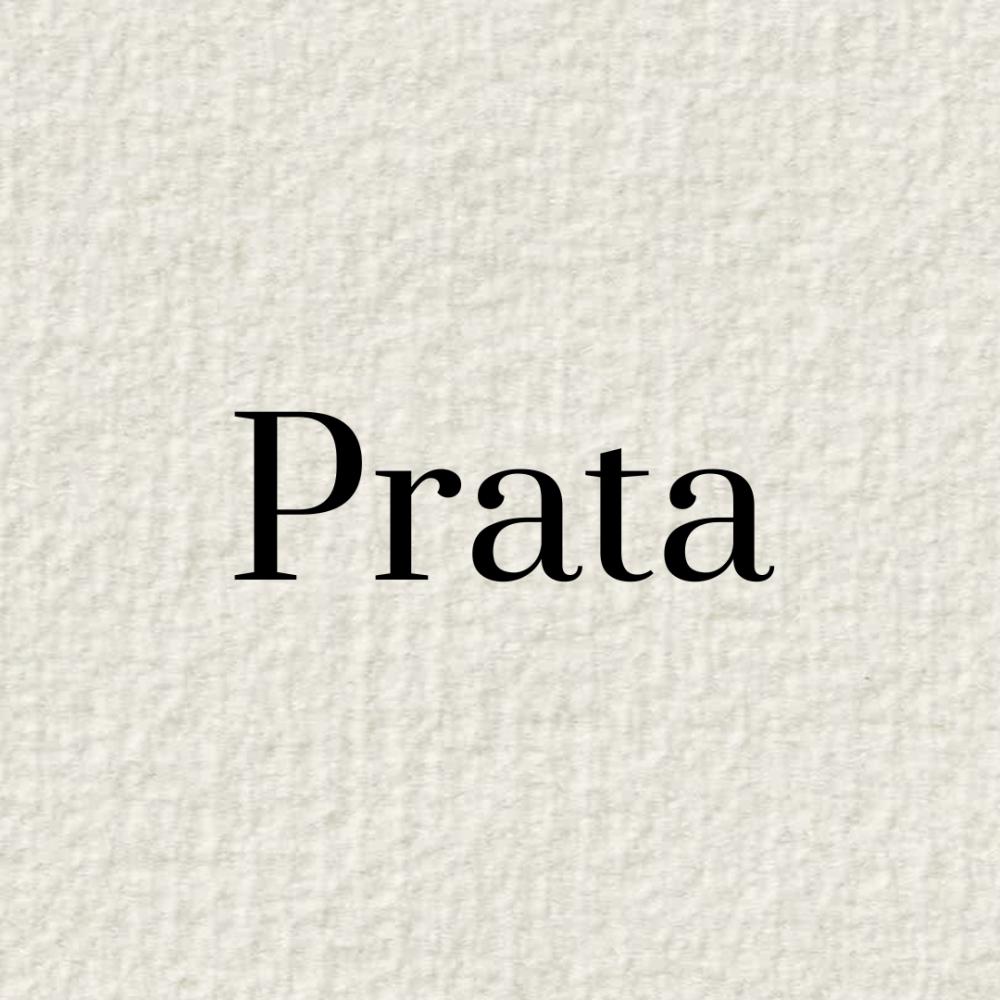
Ilustrasi font canva (dok. Canva) Prata adalah font sans-serif dengan elemen dekoratif yang memberikan sentuhan klasik pada setiap desain. Dengan ketebalan dan proporsi huruf yang seimbang, Prata memberikan kesan profesional dan modern. Cocok digunakan untuk merek yang ingin terlihat trendi namun tetap eksklusif.
3. Niconne
Ilustrasi font canva (dok. Canva) Niconne membawa kita kembali ke era keemasan desain klasik. Font ini memberikan kesan mewah dengan huruf bergaya kapital yang meliuk-liuk. Niconne sangat ideal untuk merek yang ingin memberikan nuansa vintage dan bergaya, menciptakan kesan timeless yang sulit dilupakan.
4. The Seasons
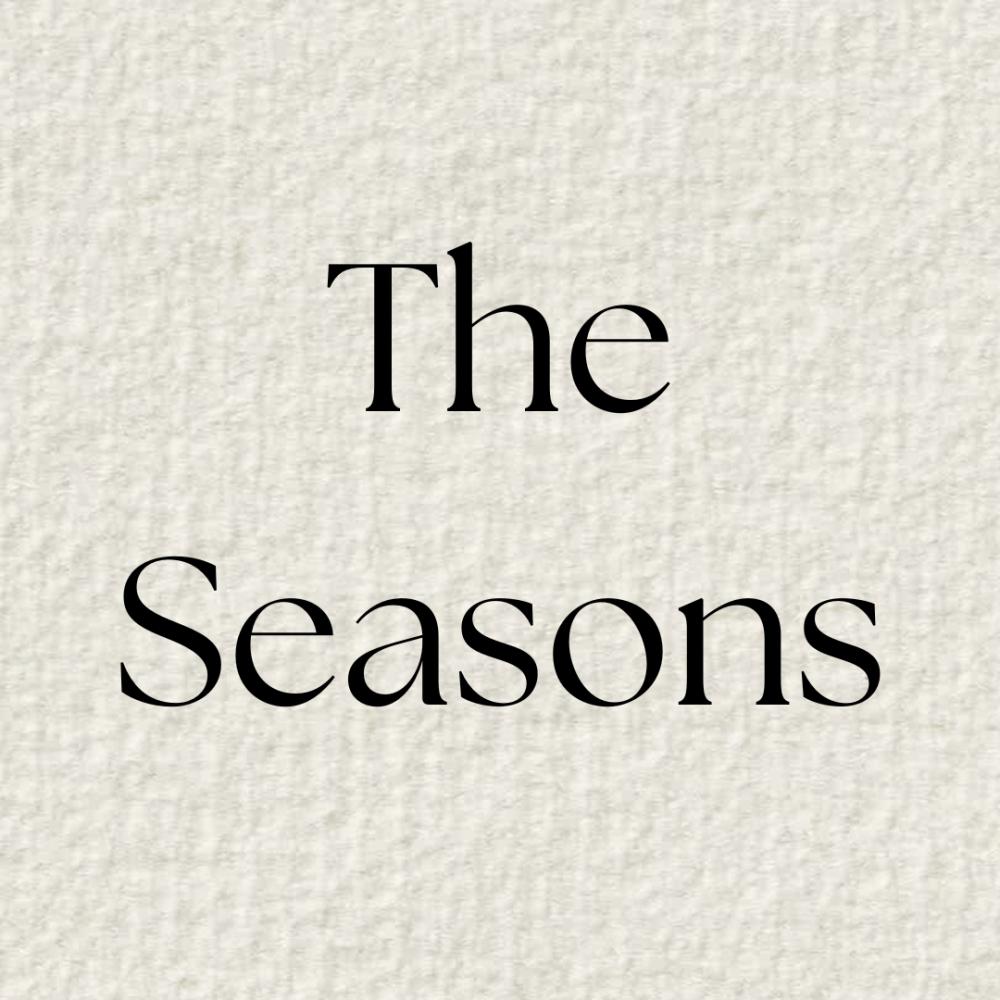
Ilustrasi font canva (dok. Canva) The Seasons hadir dengan keindahan yang unik. Meskipun memiliki unsur-unsur klasik, font ini tetap memiliki keluwesan dalam desain. Hal ini memungkinkan penggunaan yang kreatif dan penyesuaian untuk berbagai kebutuhan merek tanpa kehilangan esensi kemewahan.
5. Pinyon Script
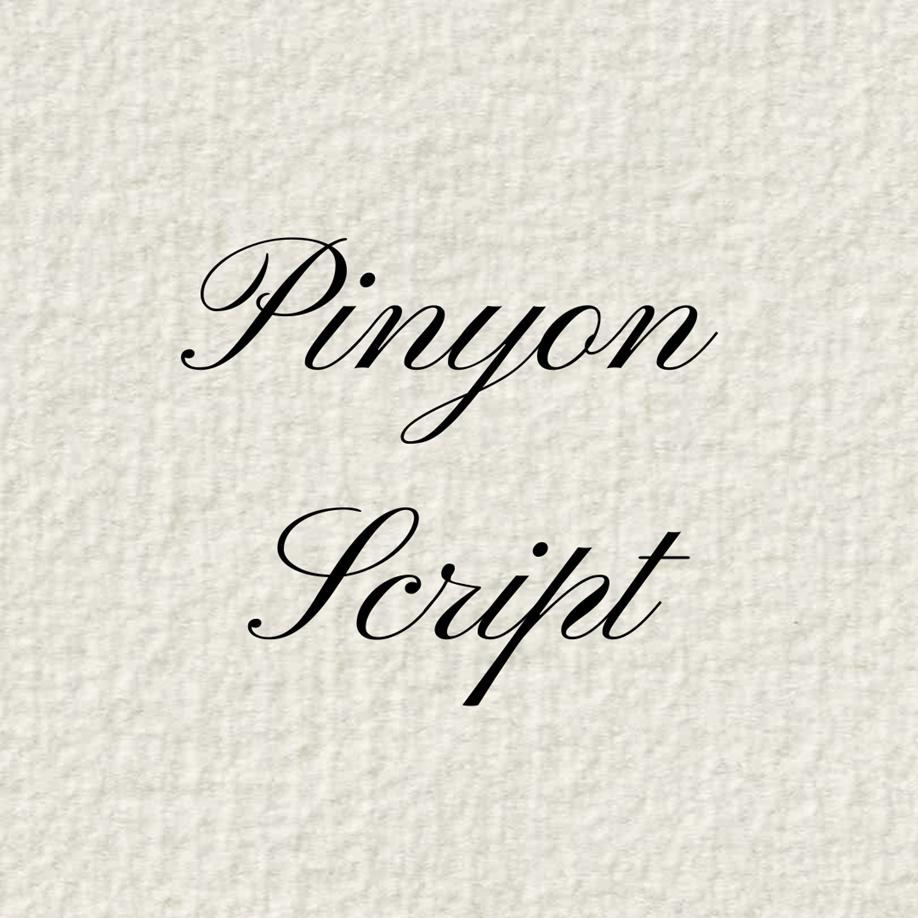
Ilustrasi font canva (dok. Canva) Pinyon Script adalah font berseni tinggi yang memberikan sentuhan klasik dan anggun pada desain. Dengan gaya kaligrafi yang indah, Pinyon Script cocok untuk merek yang ingin terlihat romantis dan berkelas. Penggunaan Pinyon Script pada brand-mu akan memberikan kesan personal dan eksklusif.
6. Afrah
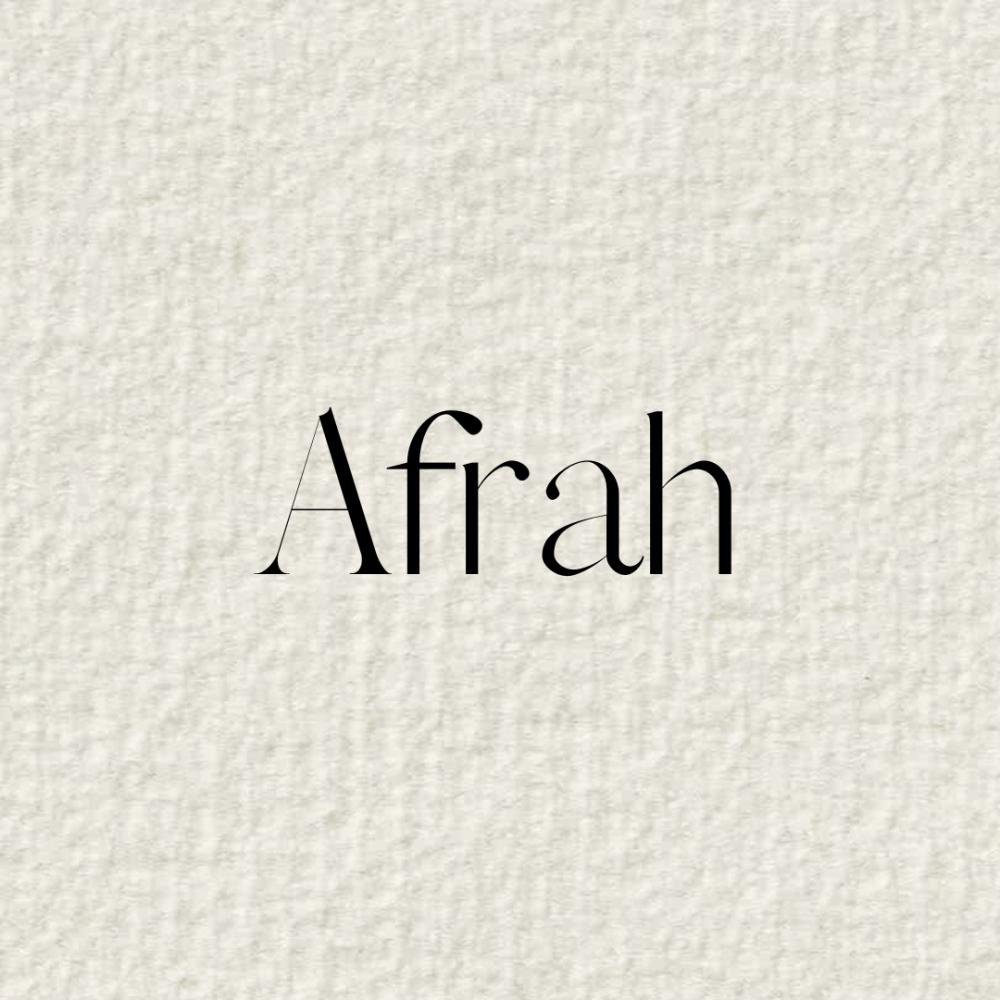
Ilustrasi font canva (dok. Canva) Afrah adalah font yang menggabungkan unsur modern dan klasik. Dengan detail yang halus dan linier yang bersih, Afrah memberikan kesan minimalis namun tetap mewah. Cocok digunakan oleh merek yang ingin terlihat eksklusif namun tetap mempertahankan kesan kontemporer.
Membuat brand-mu terlihat mewah bukanlah pencitraan, tetapi merupakan strategi bisnis yang dapat membuka peluang baru. Ketika kamu membuat bisnis-mu terlihat mewah maka nilai bisnismu akan meningkat, daya tarik brand-mu juga lebih kuat dan juga dapat menarik segmen pasa ekslusif. Dengan menggunakan salah satu dari ke-6 font Canva di atas, kamu dapat meningkatkan citra merek dan memberikan kesan kemewahan yang akan melekat lebih lama dalam ingatan konsumen.